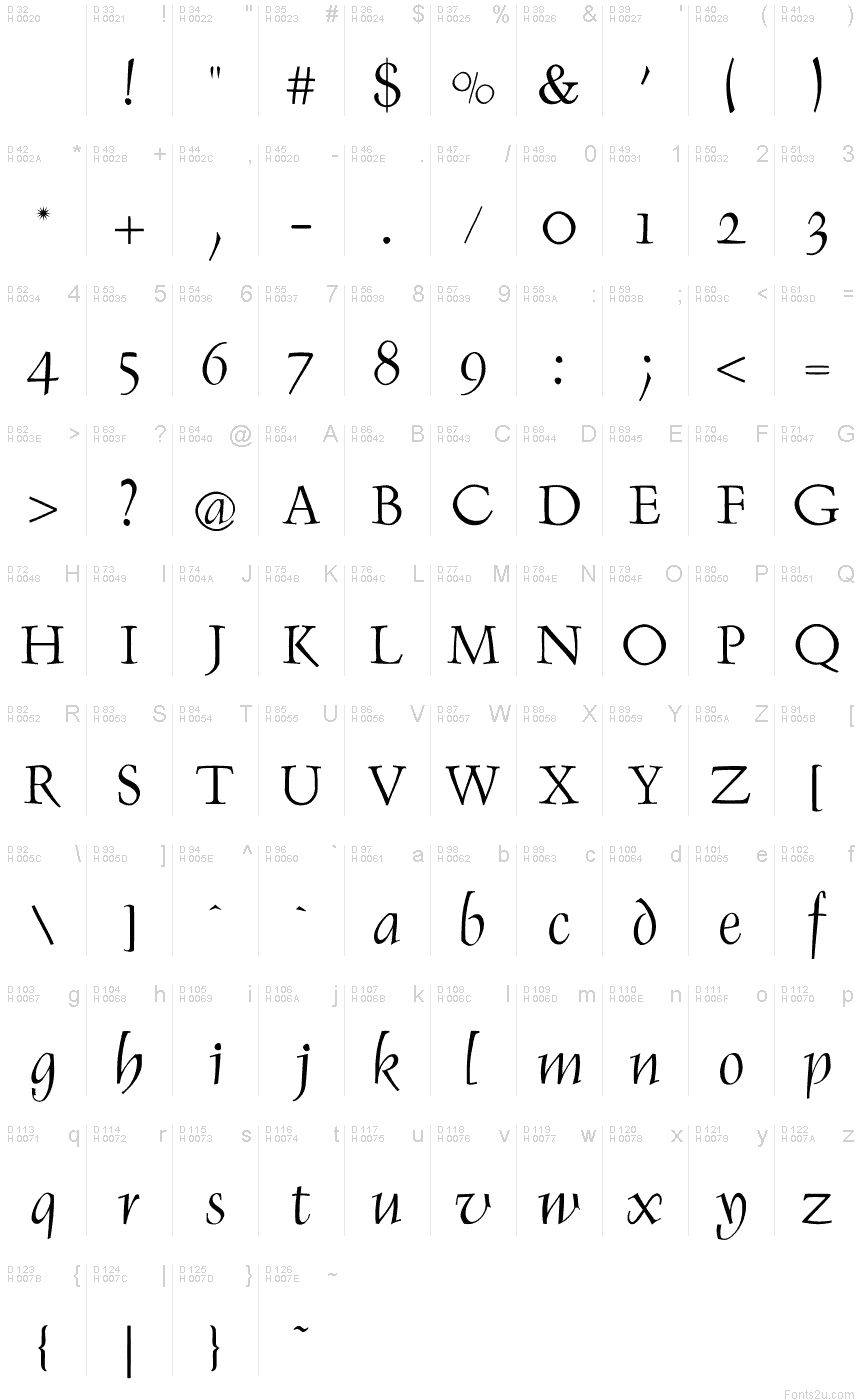
Renaiss Italic autorstwa M. Klein to darmowy, renesansowy krój szeryfowy w wersji kursywnej, o lekkim, literackim rytmie. Litery pochylają się i płyną z kaligraficzną swobodą, łącząc ostre, klinowate szeryfy z długimi, pełnymi gracji pociągnięciami. Dzięki temu font zyskuje elegancję dawnych ksiąg, unikając przy tym sztywności formalnych grawerunków.
Idealnie sprawdza się na okładkach tomików poezji, w oprawie graficznej wystaw historycznych, na etykietach win, w cytatach redakcyjnych oraz nagłówkach, gdzie potrzeba odrobiny klimatu epoki. Jako darmowy font, świetnie pasuje także do krótkich haseł brandingowych, zaproszeń i otwarć rozdziałów – zwłaszcza gdy zależy Ci na zwiewnym, ręcznym ruchu, przy jednoczesnym zachowaniu charakteru pisma szeryfowego.